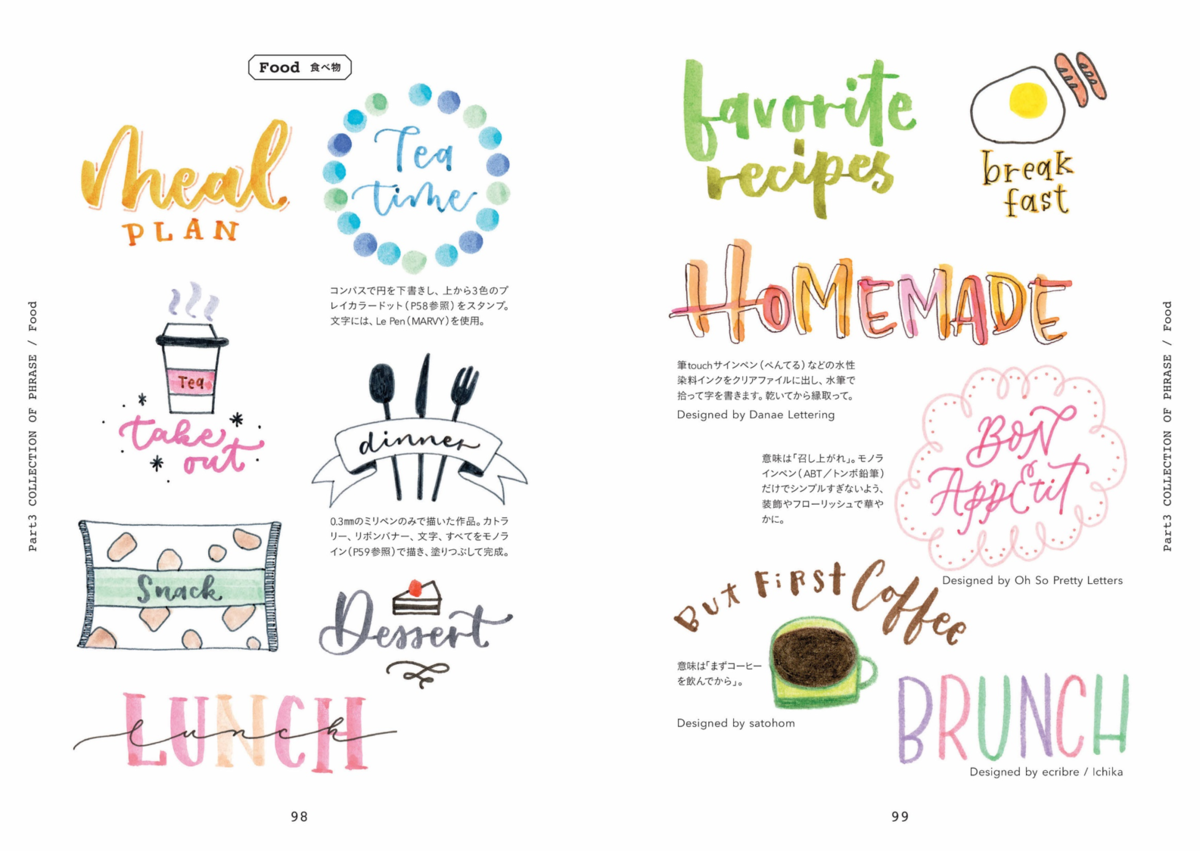
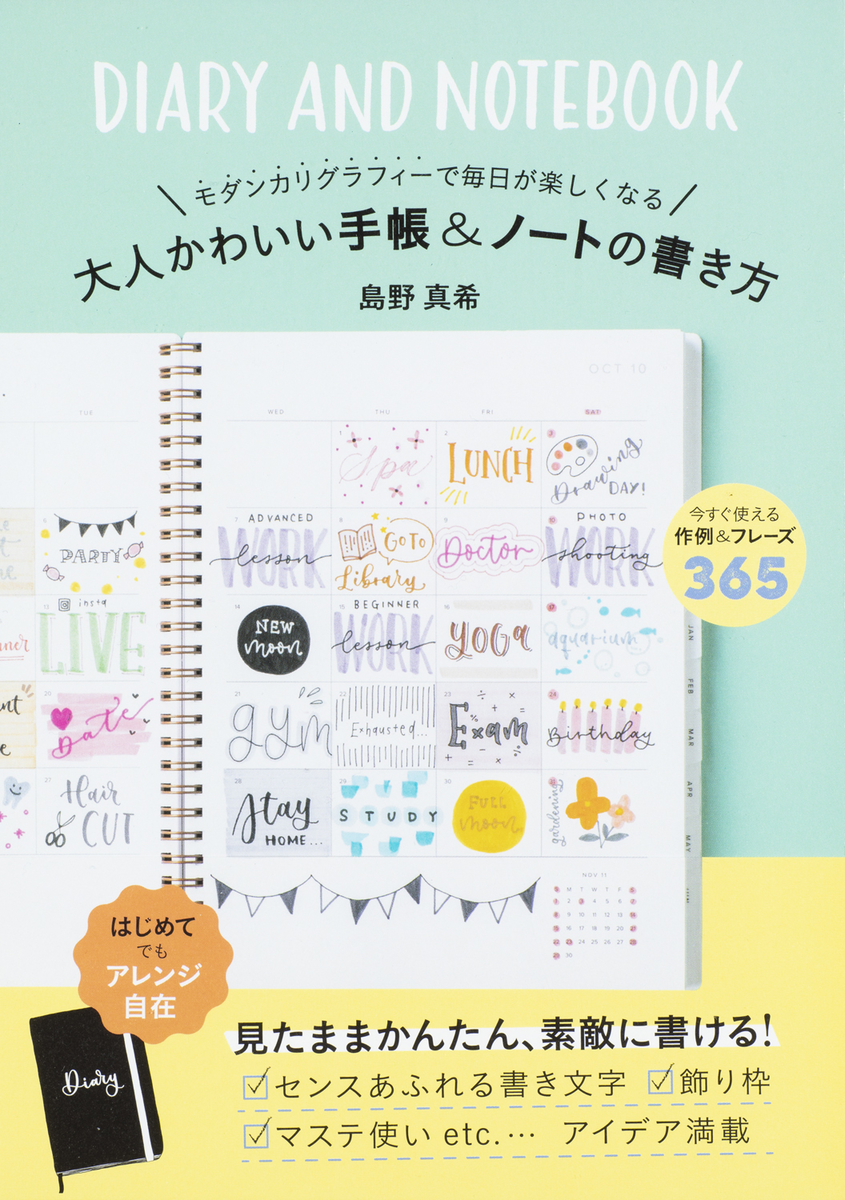
大人かわいい手帳&ノートの書き方 モダンカリグラフィーで毎日が楽しくなる
世界文化社は2020年11月13日(金)に日本の「モダンカリグラフィー」第一人者・島野真氏が教える毎日が楽しくなるオリジナル手帳のアイデアが満載の手帳術書籍「大人かわいい手帳&ノートの書き方 モダンカリグラフィーで毎日が楽しくなる」を発売した。
手帳好き&レタリング好き必見! 初心者でも簡単に始められる「大人かわいい手帳&ノートの書き方 モダンカリグラフィーで毎日が楽しくなる」
近年、デジタルデバイスの発展により、スケジュールやタスクなどをすべてアプリ上で管理することがスタンダードになってきた。
簡単に管理することができ、人との共有も容易だが、そんな時代でもあえて自分自身の手で書き、思考整理をするために手帳やノートを使う人が増えている。
本書「大人かわいい手帳&ノートの書き方 モダンカリグラフィーで毎日が楽しくなる」では日本のモダンカリグラフィーの第一人者である島野真希氏が、初心者でも簡単に、マネするだけでかわいく書ける手帳術をレクチャーしてくれる。
定番のスケジュール帳はもちろん、マイノート、トラッカー、旅ノート、夢ノートなど、毎日が楽しくなるようなオリジナル手帳の作例をたっぷり紹介。
筆ペンで書くモダンカリグラフィーや、普通のペンで書けるハンドレタリングで飾れば、開くたびにワクワクする手帳が作れます。日々の「書く」ことがより楽しく、より心を豊かにする一冊となる。
「大人かわいい手帳&ノートの書き方 モダンカリグラフィーで毎日が楽しくなる」特徴
手帳にそのまま使えるフレーズ例
どんなフレーズにも使える文字のアレンジ方法
見出しの飾りバリエーション
絵心がなくても描けるイラスト作例
空いてしまったスペースの活用法 etc.
「大人かわいい手帳&ノートの書き方 モダンカリグラフィーで毎日が楽しくなる」の冒頭には楽しい手帳ライフを送るための島野さん流のルールを紹介。書いていて楽しくなる、あとで見返してもワクワクする。本書はそんな手帳が作れるアイデアが満載。
まっさらなノートにマス目を書き、まわりにマスキングテープを貼ってからカラーペンで日付や曜日を記入。マステを活用することで、予定をたくさん書き込まなくてもにぎやかになる。
旅先での記憶を辿りながら、写真を貼ったり、感じたことを書いたりしながら思い出や旅のスケジュールを記録。見返すたびに、楽しい思い出がよみがえる。
タイトルに使える大きくて読みやすいデザインから、アイコンとしても使えるイラストを組み合わせたデザインまで、手帳やノートを開くのが楽しくなる、かわいいフレーズや飾りを掲載。
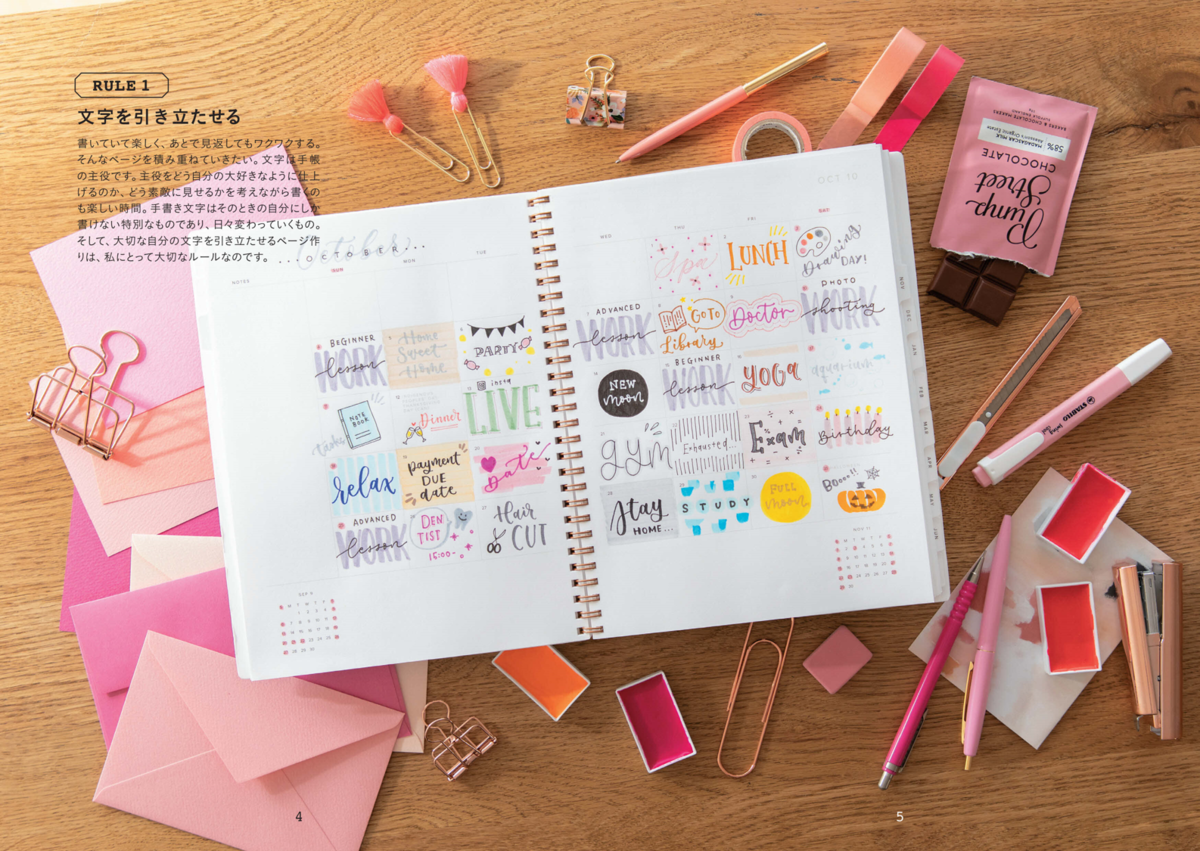
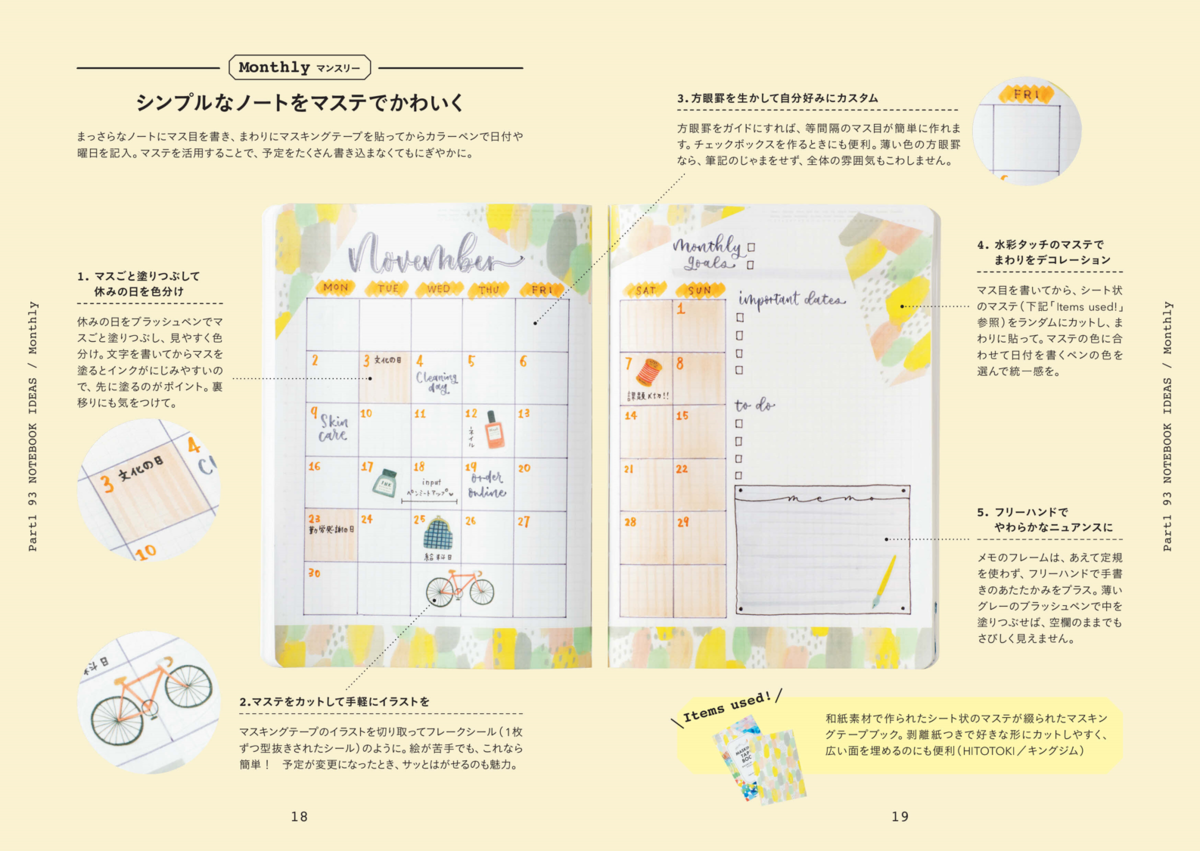
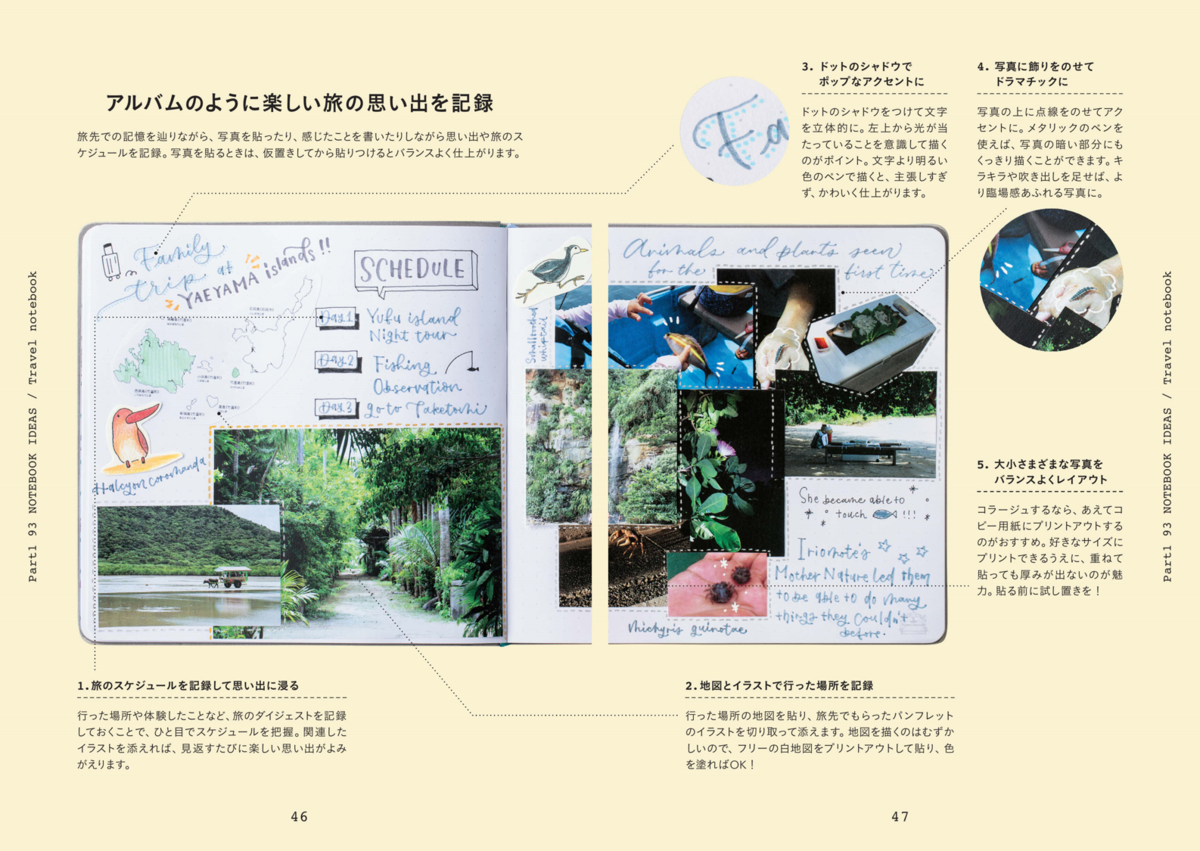
「大人かわいい手帳&ノートの書き方 モダンカリグラフィーで毎日が楽しくなる」目次
Part1 モダンカリグラフィーで綴る手帳&ノートアイデア93
Part2 モダンカリグラフィーの書き方とフォント
Part3 手帳にそのまま使えるフレーズと飾り集